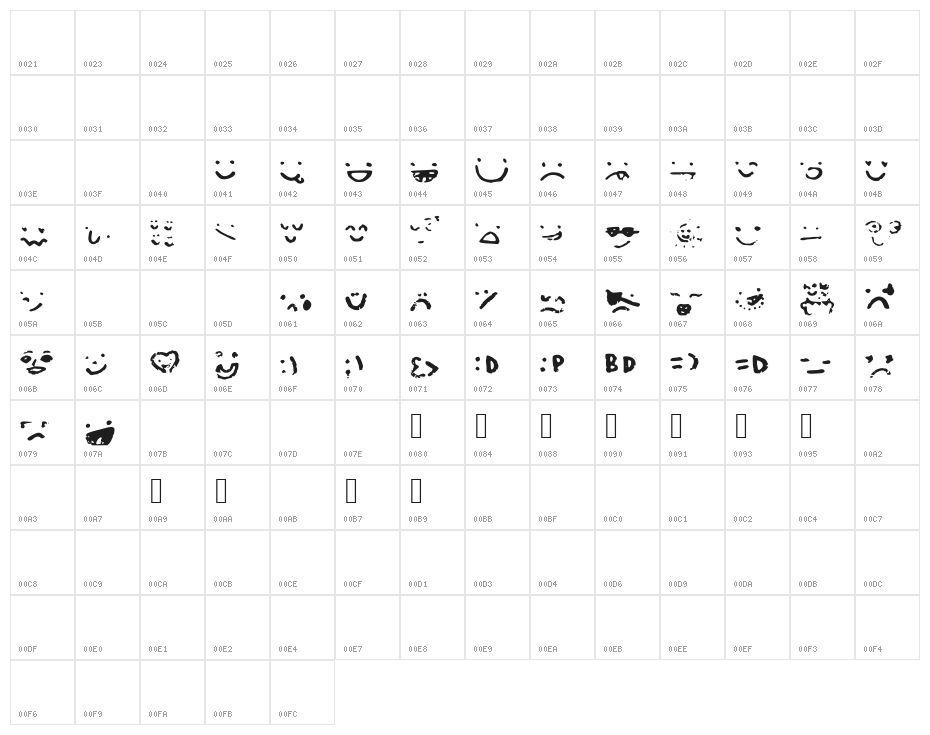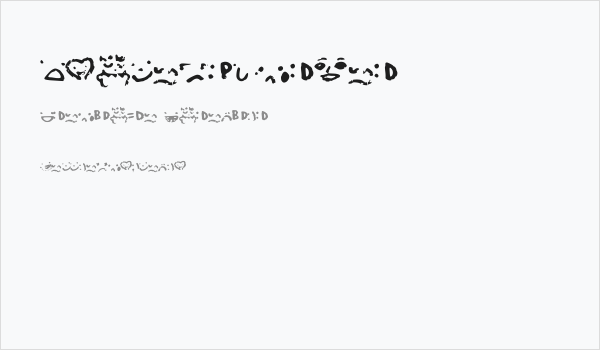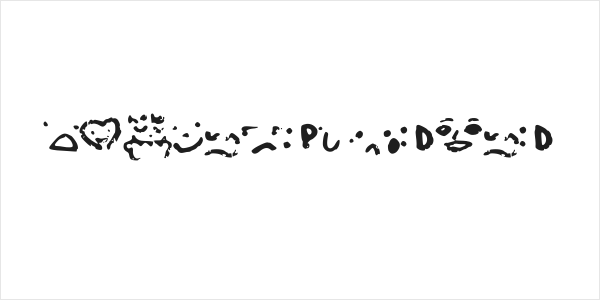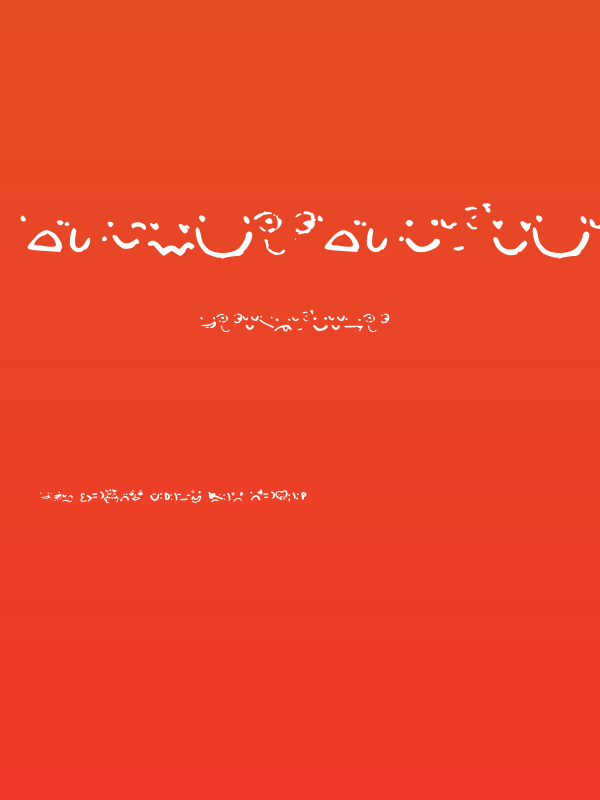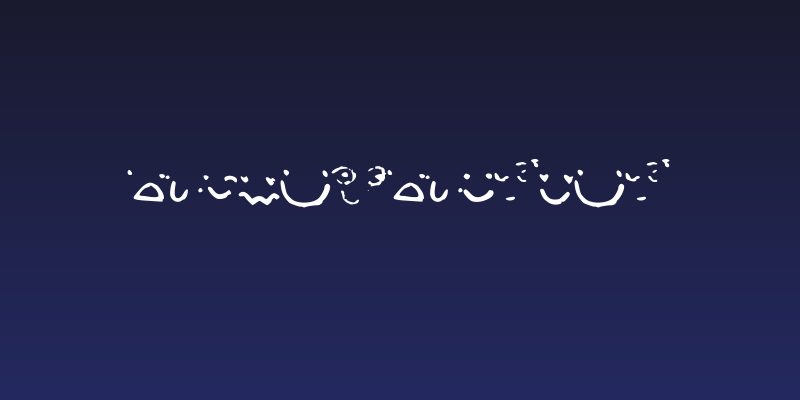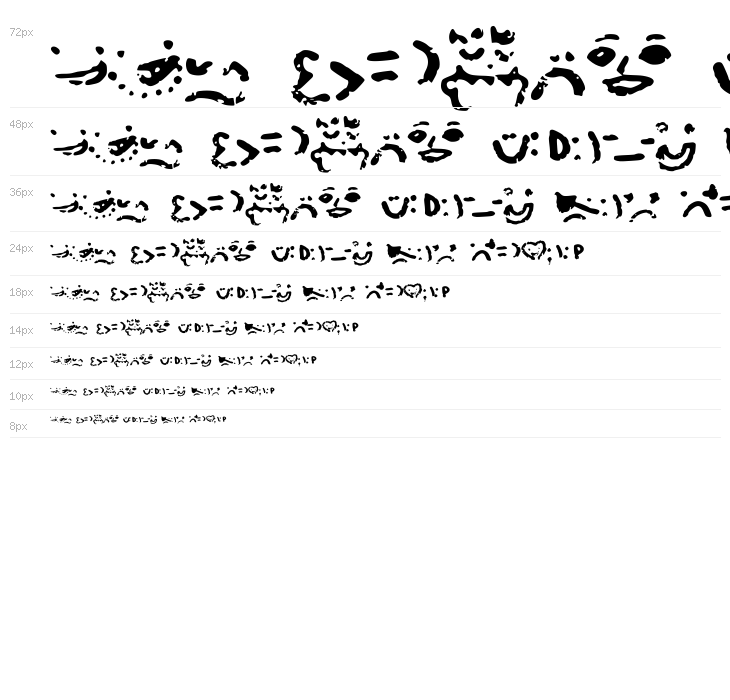
SmileysMarker Font
| Stile generale | Playful, Whimsical, Decorative |
| Caso d'uso | Decorative elements, Greeting cards, Children's materials |
| Progetti proposti | Ideal for children's books, greeting cards, playful branding, and any project needing a fun, whimsical touch. |